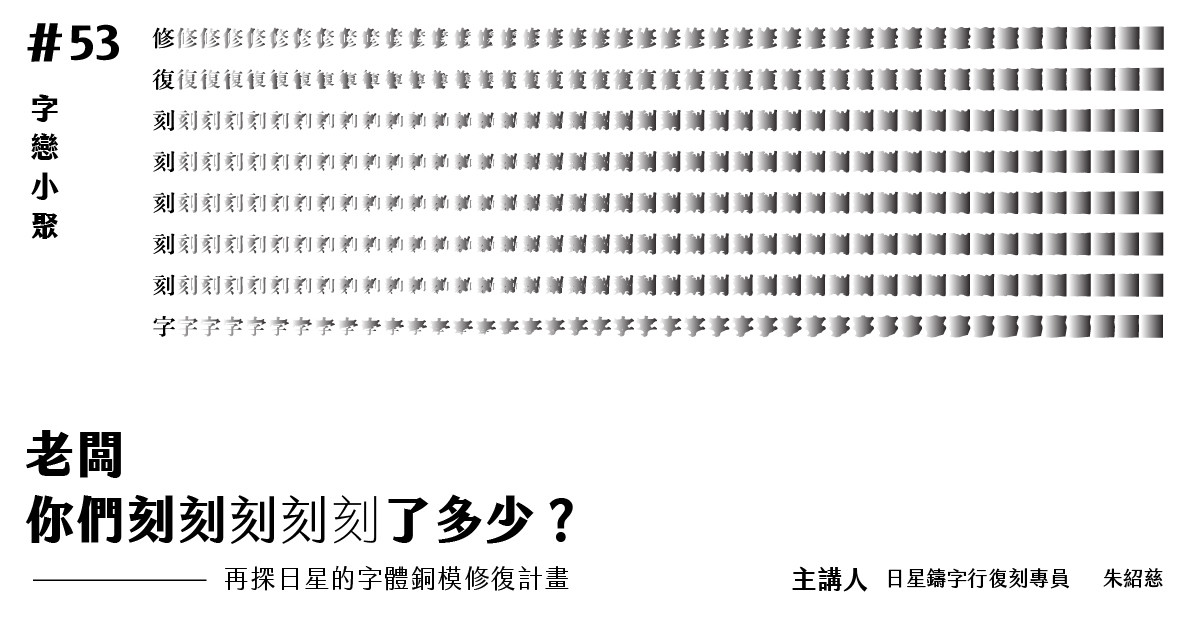
2016 年底,日星鑄字行成功透過群眾集資籌得一筆資金,準備要讓許多年久失修的鉛字銅模「復活」。如今,日星從頭開始手把手訓練的專業修復員—紹慈,經過好一段時間的學習,已經初步掌握了修復字體的眉角。在銅模修復計畫進入第二個年度的現在,我們來聽聽紹慈為我們介紹這些日子以來經歷了什麼樣的考驗,也為還不熟悉這個議題的朋友介紹「字體修復」到底是怎樣的一件事。
朱邵慈,1991年生。2017 年接觸字體設計。目前任職於日星鑄字行字體銅模修復組。入行一年,深深覺得「字體修復」橫跨傳統與現代,初來乍到時,每天都與不同術語交手落敗,現在覺得似乎好一點了。